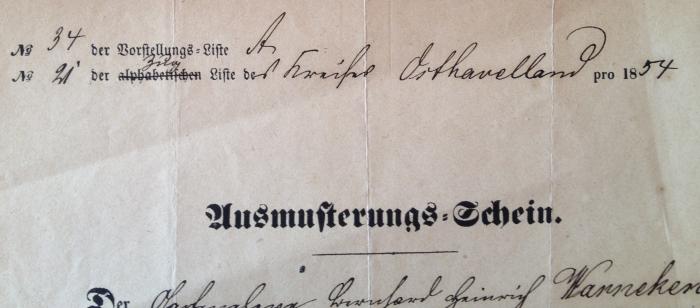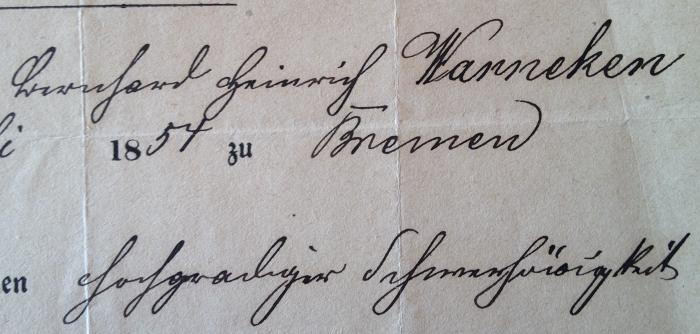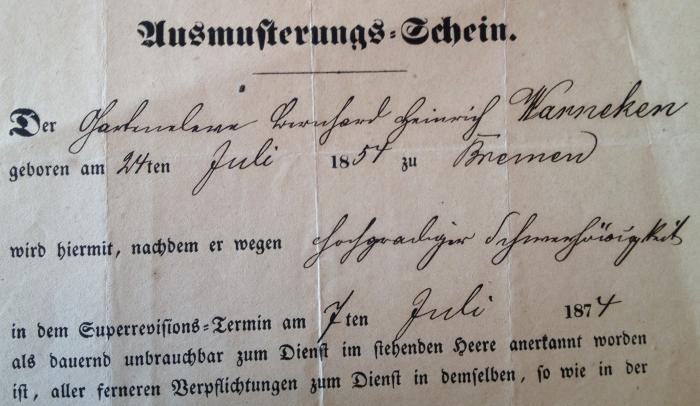
"Übersetzung" Kurrentschrift - Ausmusterungsschein
Habe mir gestern aus der Spontanität heraus diesen Ausmusterungsschein für nen Euro gekauft. Es bereitet mir aber wirklich Probleme zu entziffern was da steht.
Aus den beiden oberen Zeilen würde ich gerne wissen was vor (Ziffer) und über dem durchgestrichenen "alphabetischen" steht und zudem welcher Buchstabe nach "Vorstellungs-Liste" kommt. Der Rest müsste "des Kreies Havelland" heißen.
Die Zeile unter "Ausmusterungs-Schein" lässt mich wirklich rätseln. Ich glaube, dass der Nachname "Wanneken" ist, muss aber nicht stimmen. Falls es hilft: In der Regel sollte hier wohl erst die Tätigkeit und dann der Name stehen.
Als letztes würde ich gerne noch den Ausmusterungsgrund erfahren. Das erste Wort ist wohl "hochgradiger ...". Aber bei dem danach finde ich nichts Sinnhaftes.
Was ich jedoch auf Anhieb lesen konnte (der Nachname, sowie die Ortsangabe Bremen sind in Lateinschrift, wie damals zur Auszeichnung üblich)
Der ausgemusterte hieß Heinrich Warneken, und wurde wegen "hochgradiger Schwerhörigkeit" ausgemustert, wobei das S in Schwerhörigkeit kein richtiges Kurrent-S ist, sondern irgendwie aus der Lateinschrift da hineingeratten ist.
Beim Dienstgrad des Soldaten rätsele ich noch etwas, ebenso wie die wahrscheinlich abkürzung über dem durchgestichenen "alfabetischen". Was für eine Liste da gemeint ist, wussten wohl nur die Militärs dieser Zeit.
Zug-Liste des Kreises Osthavelland
(geb. zu) Bremen
(der Beruf, nicht Dienstgrad:) Garteneleve Bernhard Heinrich Warneken
hochgradiger Schwerhörigkeit
Das "Garten" von Garteneleve hatte ich auch schon vermutet, aber die Bezeichnung "Eleve" für Lehrling/Schüler war mit bisher unbekannt. Mal wieder was gelernt. Top, dass ihr den Namen entziffern konntet, gleich gefunden:
"Schwerhörigkeit" macht jetz auch sinn wenn man die nach rechts verschobenen Punkte betrachtet.
Nur das "Zug-Liste" Zweifel ich noch an. Schaut mich mich wie eine Abkürzung im Schema "AaBb" aus. Da vielleicht noch Ideen?
Der erste Buchstabe ist sicher ein Z, der Zug sollte schon stimmen.
... und der letzte eindeutig ein "g" und und der dekorative Schwung über der Welle macht aus der Welle ein "u".